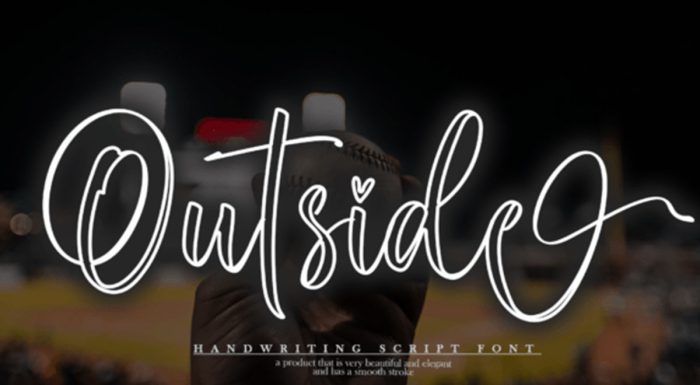
فونت Outside انگلیسی
دانلود فونت Outside انگلیسی Font اوتساید |
| ⭐ مجموعه فونت | دانلود فونت انگلیسی خارج از Font Outside |
| ⭐ توضیحات | بیرون یک فونت دست نویس زیبا، همه کاره و انعطاف پذیر است. این فونت گرم، عاشقانه و شاد، هر یک از ایده های پروژه شما را به آثار هنری واقعی تبدیل می کند. این فونت دارای کد PUA است که به این معنی است که شما می توانید به راحتی به تمام حروف و لغات دسترسی داشته باشید، این فونت با پشتیبانی از زبان کامل است! |